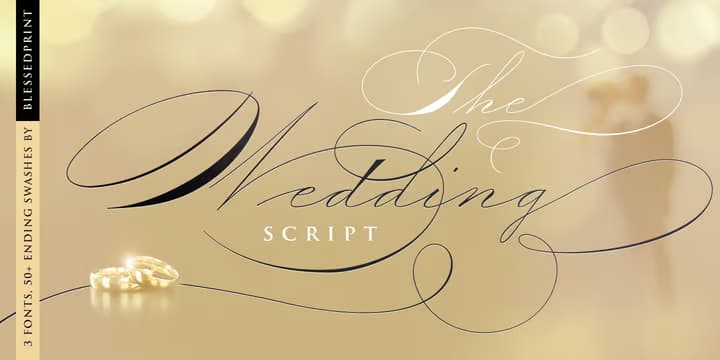
The Wedding Script
大変優雅なスペンサリアンスタイルのカッパープレートスクリプト。ウェイトの太い部分はあるものの、ストロークの大半がヘアラインの繊細なカッパープレートで、スワッシュオルタネートが充実しており、総グリフ数は2000を超えるという非常にバリエーション豊かな書体である。カッパープレートスクリプトは繊細さが重要なので、大きくしてしまうとヘアライン部が太くなって看板などには向いてないが、これはかなり細いので大きめに使っても大丈夫だろう。太いウェイトもあるので、カードなどに小さく使うのにも使えるという優秀な書体。もうすぐジューンブライドなので(ウソでしょ…)いかがでしょうか。